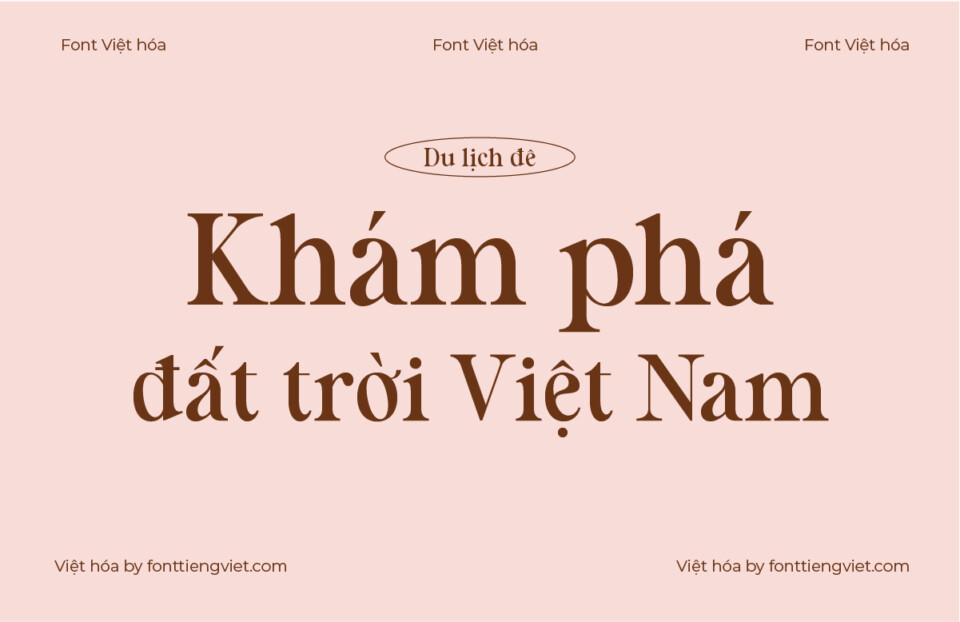
Font Việt hóa 1FTV VIP Scarlet Bradley Regular
Giới thiệu về Font Việt hóa 1FTV VIP Scarlet Bradley Regular
Trong thế giới đồ họa hiện đại, việc tìm kiếm một bộ Font Miễn Phí chất lượng cao và hỗ trợ đầy đủ tiếng Việt luôn là ưu tiên hàng đầu của các nhà thiết kế. Font Việt hóa 1FTV VIP Scarlet Bradley Regular là một trong những lựa chọn tuyệt vời nhất dành cho những ai yêu thích phong cách thanh lịch, cổ điển nhưng không kém phần hiện đại. Bộ font này không chỉ mang lại vẻ đẹp thẩm mỹ mà còn đảm bảo tính ứng dụng cao trong nhiều loại dự án khác nhau. Với sự tinh tế trong từng đường nét, Scarlet Bradley giúp các tác phẩm trở nên có hồn và thu hút người xem hơn bao giờ hết.
Đặc điểm nổi bật của Font Việt hóa 1FTV VIP Scarlet Bradley Regular
Điểm ấn tượng nhất của bộ font này chính là sự cân bằng hoàn hảo giữa các nét thanh và nét đậm. Điều này tạo nên một cảm giác dễ chịu cho mắt người đọc, đặc biệt là khi trình bày các đoạn văn bản dài hoặc tiêu đề trang trọng. Phiên bản Việt hóa bởi đội ngũ 1FTV đã được tinh chỉnh tỉ mỉ, đảm bảo các dấu câu tiếng Việt không bị lỗi hiển thị hay lệch hàng, giúp quy trình làm việc của bạn trở nên mượt mà và chuyên nghiệp hơn rất nhiều.
Ứng dụng thực tế của Font Việt hóa 1FTV VIP Scarlet Bradley Regular trong thiết kế
Nhờ vào diện mạo sang trọng, Font Việt hóa 1FTV VIP Scarlet Bradley Regular thường xuyên được ưu tiên sử dụng trong các mẫu thiết kế thiệp mời đám cưới, bìa sách nghệ thuật hoặc các ấn phẩm truyền thông cho các nhãn hàng thời trang cao cấp. Khả năng biến hóa linh hoạt giúp nó phù hợp với cả môi trường in ấn truyền thống lẫn hiển thị trên nền tảng kỹ thuật số. Khi kết hợp với các tông màu trầm hoặc màu vàng kim, bộ font này sẽ thực sự tỏa sáng và nâng tầm giá trị cho thương hiệu của bạn.
Tổng kết về giá trị của Font Việt hóa 1FTV VIP Scarlet Bradley Regular
Có thể khẳng định rằng, việc lựa chọn đúng kiểu chữ đóng vai trò quyết định đến thành công của một bản thiết kế. Với sự xuất hiện của Font Việt hóa 1FTV VIP Scarlet Bradley Regular, bạn đã có thêm một vũ khí sắc bén trong kho tàng sáng tạo của mình. Sự kết hợp giữa nét chữ uyển chuyển và sự chuẩn chỉ trong bộ gõ tiếng Việt chắc chắn sẽ làm hài lòng ngay cả những khách hàng khó tính nhất. Đừng bỏ lỡ cơ hội trải nghiệm và tải ngay bộ Font Miễn Phí, Font Việt Hóa, Font Việt hóa 1FTV VIP Scarlet Bradley Regular để bắt đầu hành trình sáng tạo những tuyệt tác nghệ thuật của riêng mình ngay từ bây giờ.